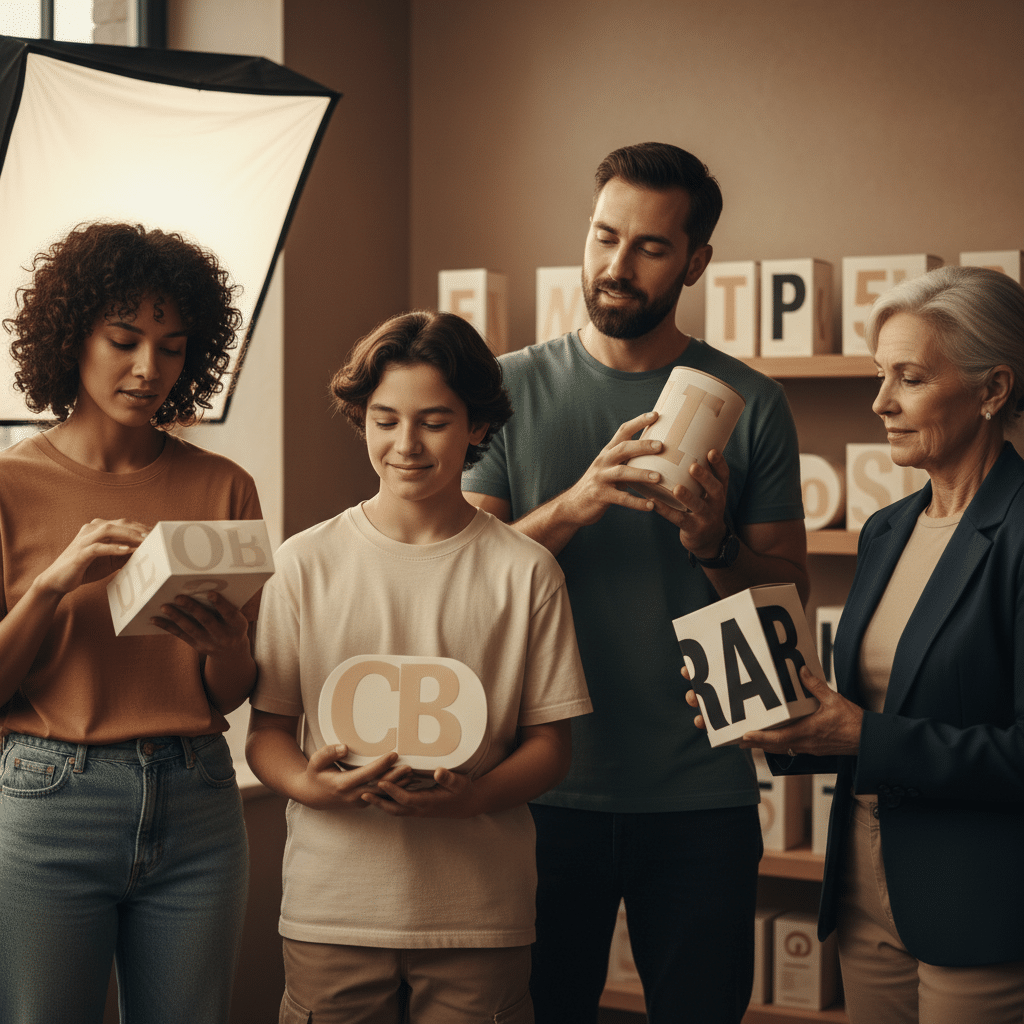
จิตวิทยาฟอนต์: เลือกใช้บนฉลากสินค้ายังไงให้ยอดขายพุ่ง
การเลือกรูปแบบตัวอักษร หรือ ฟอนต์ (Font) สำหรับฉลากสินค้า ไม่ใช่เป็นเพียงการเลือกเพื่อความสวยงาม แต่เป็นศาสตร์และศิลป์ที่ส่งผลกระทบโดยตรงต่อการรับรู้และพฤติกรรมของผู้บริโภค การทำความเข้าใจในเรื่องนี้จึงเป็นกลยุทธ์สำคัญที่สามารถช่วยยกระดับแบรนด์และกระตุ้นยอดขายได้อย่างมีนัยสำคัญ
พลังของตัวอักษรที่ส่งผลต่อการตัดสินใจซื้อ
ในภาพรวม การเลือกใช้ฟอนต์อย่างมีกลยุทธ์มีบทบาทสำคัญต่อความสำเร็จของผลิตภัณฑ์ นี่คือประเด็นสำคัญที่ควรพิจารณา:
- การสร้างการรับรู้และอารมณ์: ฟอนต์มีอิทธิพลโดยตรงต่อความรู้สึกและการรับรู้ของผู้บริโภคที่มีต่อแบรนด์ สามารถสร้างบุคลิกภาพที่แตกต่างกันได้ เช่น ความน่าเชื่อถือ ความทันสมัย หรือความหรูหรา
- บุคลิกภาพของแบรนด์: ฟอนต์แต่ละประเภทสื่อถึงบุคลิกที่แตกต่างกัน การเลือกฟอนต์ที่สอดคล้องกับแก่นแท้ของแบรนด์จะช่วยสร้างการจดจำและความผูกพันกับลูกค้าได้ดีขึ้น
- ความสอดคล้องและความอ่านง่าย: หลักการสำคัญที่สุดในการเลือกฟอนต์คือต้องสอดคล้องกับภาพลักษณ์ของแบรนด์ (Appropriateness) และต้องอ่านง่าย (Readability) เพื่อให้ผู้บริโภคเข้าใจข้อมูลบนฉลากได้อย่างรวดเร็ว
- กลยุทธ์สำหรับธุรกิจ SME: สำหรับผู้ประกอบการ SME การใช้จิตวิทยาฟอนต์เป็นเครื่องมือทางการตลาดที่ลงทุนน้อยแต่ให้ผลลัพธ์สูง สามารถสร้างความโดดเด่นบนชั้นวางและกระตุ้นการตัดสินใจซื้อได้อย่างมีประสิทธิภาพ
จิตวิทยาฟอนต์: เลือกใช้บนฉลากสินค้ายังไงให้ยอดขายพุ่ง เป็นศาสตร์ที่ว่าด้วยการศึกษาผลกระทบของรูปแบบตัวอักษร (Typography) ที่มีต่อความคิด ความรู้สึก และพฤติกรรมของมนุษย์ ในบริบทของการตลาดและการสร้างแบรนด์ ฟอนต์ทำหน้าที่เป็นมากกว่าเครื่องมือสื่อสารข้อมูล แต่เป็นองค์ประกอบสำคัญในการสร้างบุคลิกภาพและภาพลักษณ์ให้กับแบรนด์ การเลือกฟอนต์ที่เหมาะสมสำหรับฉลากสินค้าสามารถสร้างความเชื่อมโยงทางอารมณ์กับผู้บริโภค ทำให้แบรนด์เป็นที่น่าจดจำ และท้ายที่สุดคือการกระตุ้นการตัดสินใจซื้อ ณ จุดขาย
เรื่องนี้มีความสำคัญอย่างยิ่งสำหรับเจ้าของธุรกิจ โดยเฉพาะกลุ่ม SME ที่ต้องแข่งขันในตลาดที่มีสินค้ามากมาย การออกแบบฉลากสินค้าที่โดดเด่นและสื่อสารตัวตนของแบรนด์ได้อย่างชัดเจนผ่านการเลือกใช้ฟอนต์ จะช่วยสร้างความได้เปรียบและดึงดูดสายตาของผู้บริโภคได้ตั้งแต่แรกเห็น การทำความเข้าใจในหลักการของจิตวิทยาฟอนต์จึงไม่ใช่ทางเลือก แต่เป็นสิ่งจำเป็นสำหรับการสร้างแบรนด์ให้ประสบความสำเร็จในยุคปัจจุบัน
ความลับเบื้องหลังตัวอักษร: จิตวิทยาฟอนต์ทำงานอย่างไร
รูปแบบของตัวอักษรแต่ละแบบมีโครงสร้าง เส้นสาย และความโค้งมนที่เป็นเอกลักษณ์ ซึ่งสมองของมนุษย์จะประมวลผลและเชื่อมโยงลักษณะเหล่านี้เข้ากับประสบการณ์และความทรงจำเดิม ทำให้เกิดเป็นความรู้สึกและอารมณ์ที่แตกต่างกันออกไปโดยไม่รู้ตัว นี่คือกลไกพื้นฐานของจิตวิทยาฟอนต์ที่นักการตลาดและนักออกแบบนำมาใช้เพื่อสร้างอิทธิพลต่อผู้บริโภค
ฟอนต์ไม่ได้เป็นเพียงตัวอักษร แต่เป็นภาษากายของแบรนด์ที่สื่อสารกับลูกค้าก่อนที่พวกเขาจะได้อ่านข้อความเสียอีก
ตัวอย่างเช่น ฟอนต์ที่มีลักษณะหนาและหนักแน่นอาจสื่อถึงความแข็งแกร่งและความมั่นคง ในขณะที่ฟอนต์ที่มีเส้นบางและโค้งมนอาจสื่อถึงความอ่อนโยนและความสง่างาม การเลือกฟอนต์ที่เหมาะสมจึงเป็นการกำหนด “น้ำเสียง” (Tone of Voice) ให้กับแบรนด์ หากเลือกฟอนต์ที่ไม่สอดคล้องกับบุคลิกของสินค้า อาจทำให้เกิดความสับสนและลดทอนความน่าเชื่อถือได้ เช่น การใช้ฟอนต์ที่ดูสนุกสนานขี้เล่นบนฉลากสินค้าของสถาบันการเงิน อาจทำให้แบรนด์ดูไม่เป็นมืออาชีพและขาดความน่าไว้วางใจ ในทางกลับกัน การเลือกฟอนต์ที่ถูกต้องจะช่วยเสริมสร้างภาพลักษณ์ที่แข็งแกร่ง ทำให้ลูกค้ารู้สึกเชื่อมโยงและมั่นใจในแบรนด์ ซึ่งนำไปสู่การตัดสินใจซื้อที่ง่ายขึ้น
หลักการสำคัญในการเลือกฟอนต์สำหรับฉลากสินค้า
การเลือกฟอนต์สำหรับฉลากสินค้าไม่ใช่เรื่องของความชอบส่วนตัว แต่ต้องอาศัยหลักการทางจิตวิทยาและการออกแบบเพื่อให้ได้ผลลัพธ์ที่ดีที่สุด การพิจารณาองค์ประกอบต่างๆ อย่างรอบด้านจะช่วยให้ฟอนต์ที่เลือกนั้นสามารถทำงานได้อย่างเต็มประสิทธิภาพ ทั้งในแง่ของการสื่อสารและการสร้างยอดขาย
| หลักจิตวิทยา | คำอธิบาย |
|---|---|
| ความถูกต้อง (Appropriateness) | ฟอนต์ต้องสอดคล้องกับภาพลักษณ์ของแบรนด์ กลุ่มเป้าหมาย และประเภทของสินค้า เช่น แบรนด์หรูใช้ฟอนต์ Serif แบรนด์เทคโนโลยีใช้ Sans Serif |
| ความอ่านง่าย (Readability) | ฟอนต์ต้องอ่านง่าย ไม่ซับซ้อนเกินไป เพื่อให้ผู้บริโภคสามารถรับข้อมูลสำคัญ เช่น ชื่อสินค้า ส่วนประกอบ ได้อย่างรวดเร็วและชัดเจน |
| ความไม่ซ้ำซ้อน (Uniqueness) | ฟอนต์ควรมีเอกลักษณ์ที่โดดเด่นและแตกต่างจากคู่แข่ง เพื่อสร้างการจดจำและทำให้แบรนด์เป็นที่น่าสนใจบนชั้นวาง |
| ความมั่นคง (Consistency) | ควรใช้ชุดฟอนต์เดียวกันหรือสอดคล้องกันในทุกสื่อของแบรนด์ (ฉลาก, เว็บไซต์, โซเชียลมีเดีย) เพื่อสร้างภาพลักษณ์ที่แข็งแกร่งและเป็นหนึ่งเดียว |
| ความเชื่อถือได้ (Trustworthiness) | ฟอนต์บางประเภท เช่น Serif ที่ดูเป็นทางการ สามารถช่วยเพิ่มความรู้สึกน่าเชื่อถือและความเป็นมืออาชีพให้กับแบรนด์ได้ |
| การทำงานร่วมกัน (Compatibility) | ฟอนต์ที่เลือกต้องเข้ากันได้ดีกับองค์ประกอบอื่นๆ บนฉลาก เช่น สีสัน ภาพประกอบ โลโก้ และวัสดุของบรรจุภัณฑ์ |
ความสอดคล้องกับแบรนด์และความอ่านง่าย: สองหัวใจหลักที่ต้องคำนึงถึง
จากหลักการทั้งหมด “ความถูกต้อง” หรือความสอดคล้องกับแบรนด์ และ “ความอ่านง่าย” ถือเป็นสองปัจจัยที่สำคัญที่สุด ฟอนต์ที่สวยงามแต่ไม่สอดคล้องกับบุคลิกของสินค้า อาจสร้างความสับสนให้ผู้บริโภค ในขณะเดียวกัน ฟอนต์ที่มีเอกลักษณ์แต่กลับอ่านยาก จะทำให้ข้อมูลสำคัญบนฉลากถูกมองข้ามไป ซึ่งอาจส่งผลเสียต่อการตัดสินใจซื้อ ดังนั้น การสร้างสมดุลระหว่างความสวยงาม ความมีเอกลักษณ์ และการใช้งานจริงจึงเป็นสิ่งจำเป็นอย่างยิ่งในการออกแบบฉลากสินค้าให้มีประสิทธิภาพ